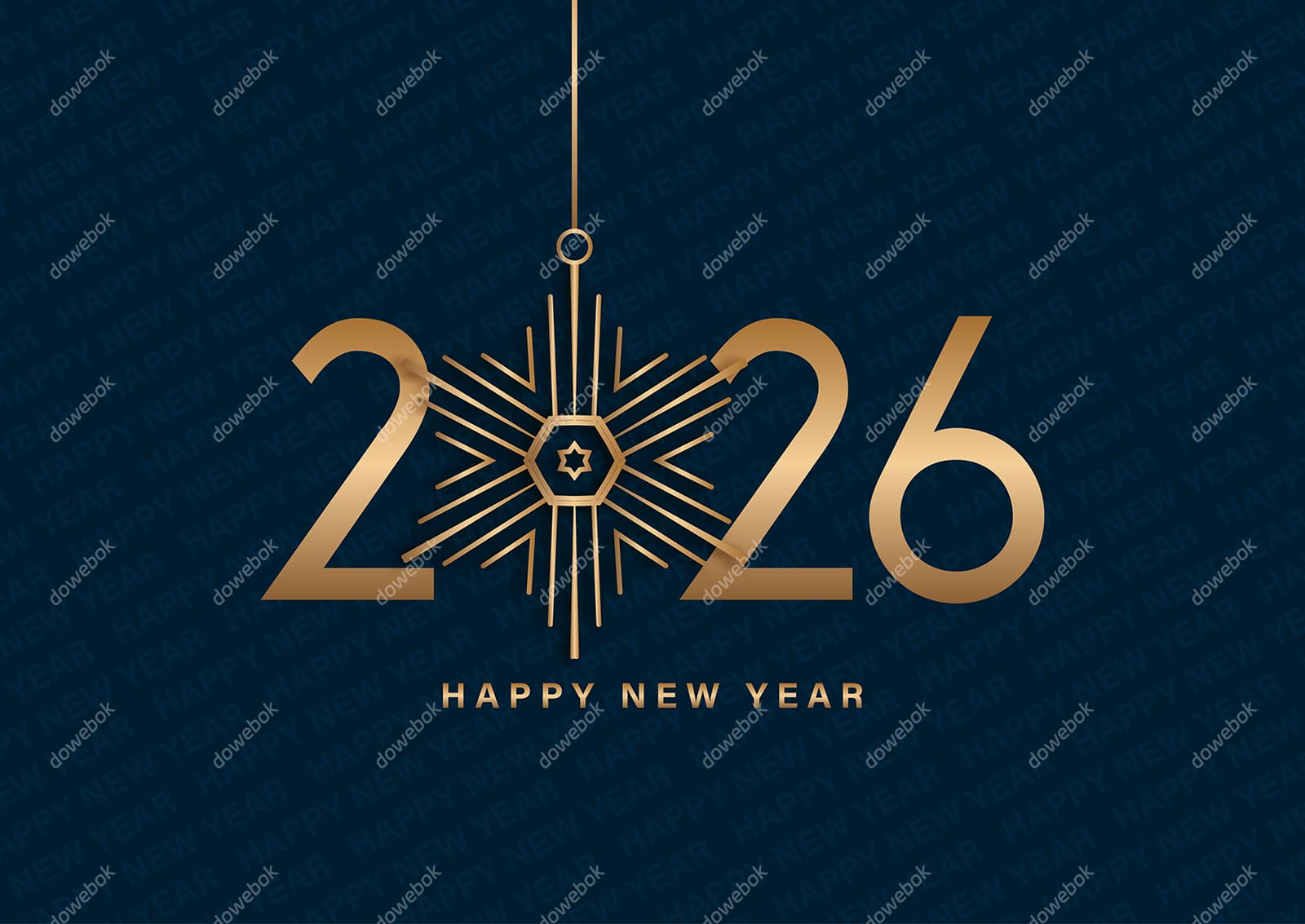
这是一款雪花装饰和数字设计的 2026 新年快乐矢量素材,深幽藏蓝背景衬出轻奢质感,鎏金 “2026” 字体间嵌着放射状星芒装饰(形似挂饰),中心缀六角星细节,精致且富有设计感。下方 “Happy New Year” 字样同色呼应,整体以蓝金配色融合星芒元素,既显跨年的雅致仪式感,又用金属质感的装饰细节烘托出节日的精致氛围,沉稳中透着亮眼格调。